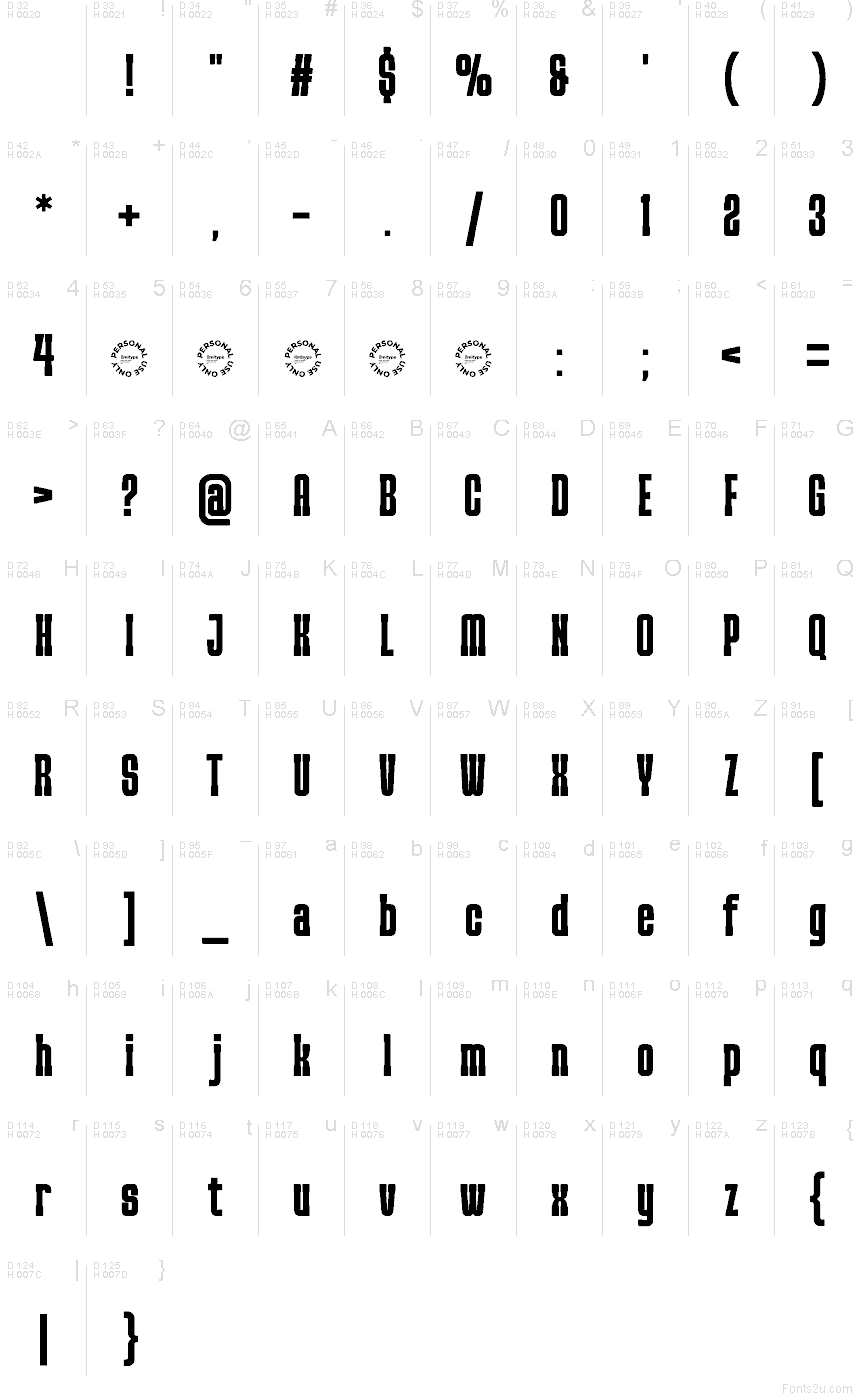
Belfrage von Limitype ist eine kostenlose Retro-Display-Schrift mit dem markanten Charakter alter Plakate. Die Lettern wirken hoch und kompakt gesetzt, mit abgerundeten Ecken, schmalen Öffnungen und einem leichten 70er-Jahre-Groove, der dem Schriftbild einen soliden, blockartigen Schwung verleiht.
Sie passt perfekt zum Branding von Cafés, Schallplatten-Covern, Verpackungen, Event-Plakaten, Magazin-Headlines und Titelkarten, bei denen es auf einen starken Auftritt bei kurzem Text ankommt. Da es sich um eine kostenlose Schrift handelt, ist sie zudem ideal für schnelle Social-Media-Grafiken oder Merch-Designs. Nutzen Sie Belfrage, wenn das Layout allein durch die Typografie getragen werden soll, denn die komprimierten Silhouetten und weichen Kanten sind bereits das ganze Statement.